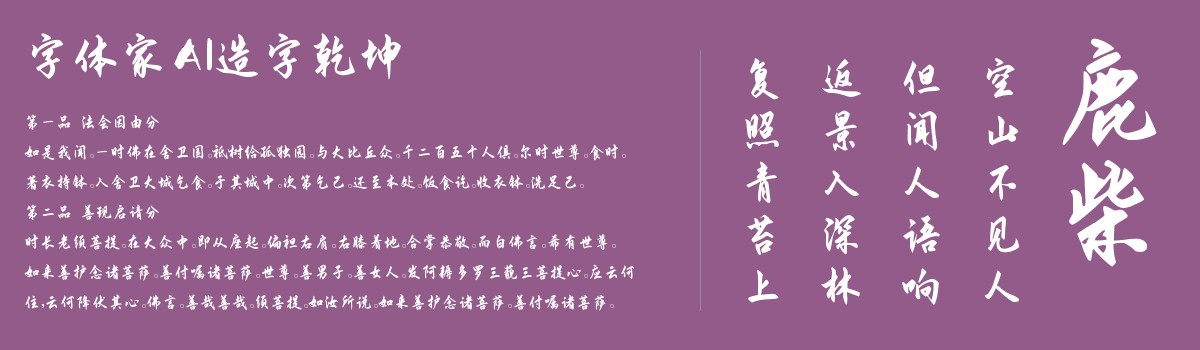
字体家AI造字乾坤
字体家AI造字乾坤是一款由字体家AI神笔造字生成的一款艺术字体,这是一款行楷风格的手写体,兼具楷书规整与行书流畅。毛笔书写质感鲜明,起笔收笔带自然顿挫,横画微右上斜,竖画挺拔;撇捺舒展,收笔尖细露锋;部分笔画有牵丝连笔,增强连贯性。结构重心稳定,疏密有致,墨色过渡自然,尽显手写的灵动韵律与端庄气度。比较适合用于艺术类装饰文字,海报、网页、广告设计,室内装饰,平面标题设计、食品包装、品牌标志等。